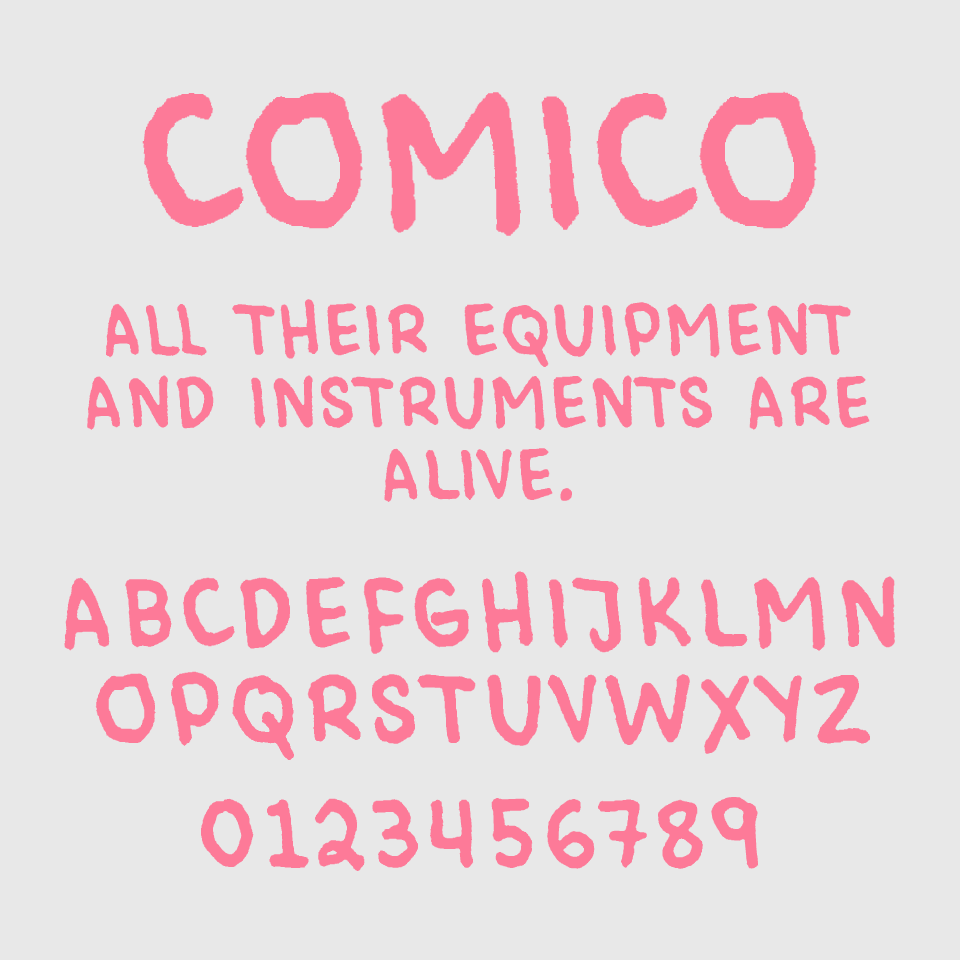
Comicoは、手描き感たっぷりのラフなアウトラインが特徴の手書き風フォントです。
線の輪郭に揺らぎがあり、まるでクレヨンで描かれたかのような質感が出ています。やわらかなリズムで構成された文字は、見る人に楽しさや親近感を感じる文字となっています。
子ども向けの絵本や、日常的なコミュニケーションにぴったりで、ポップでカジュアルな空気をつくるのにぴったりなフォントです。